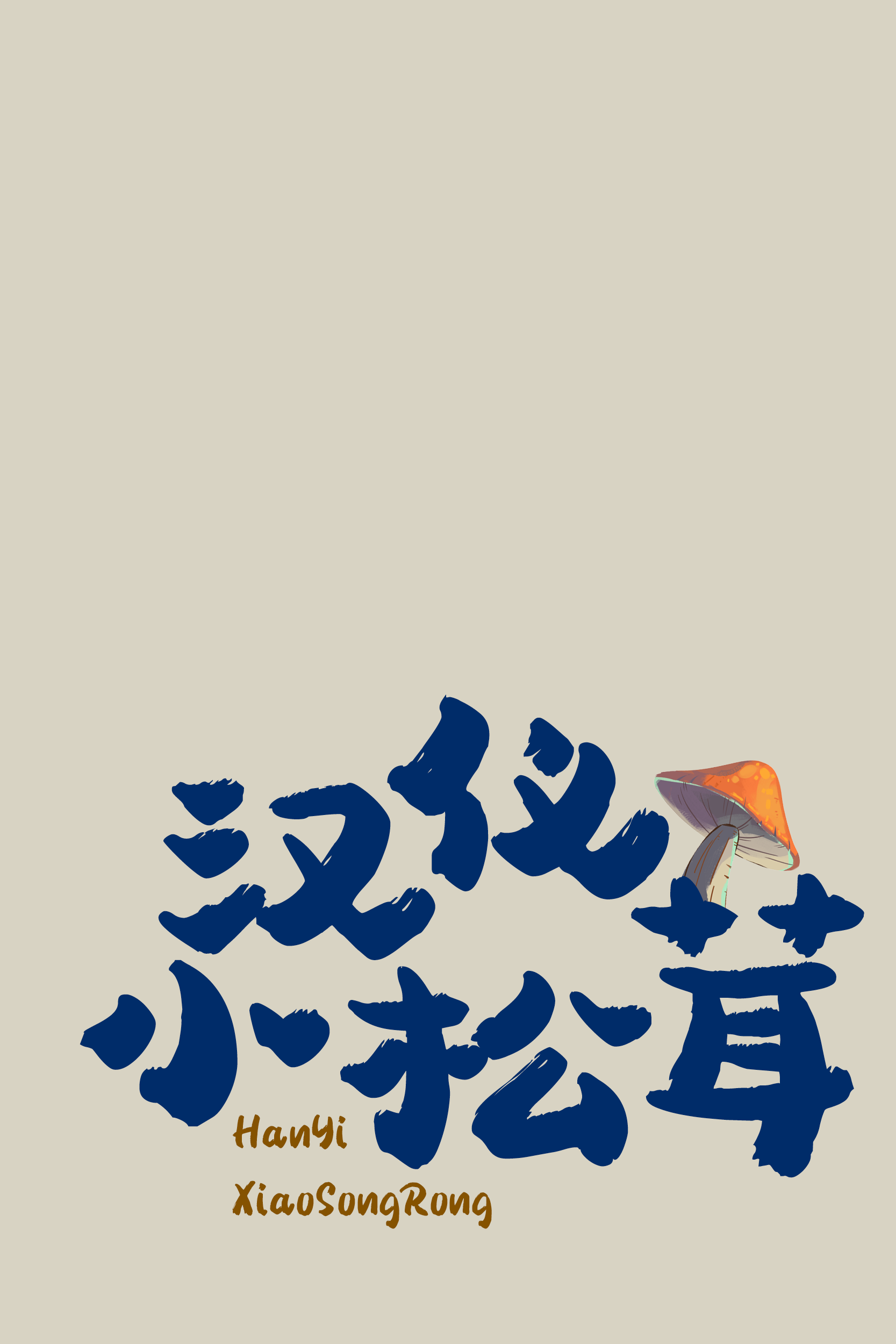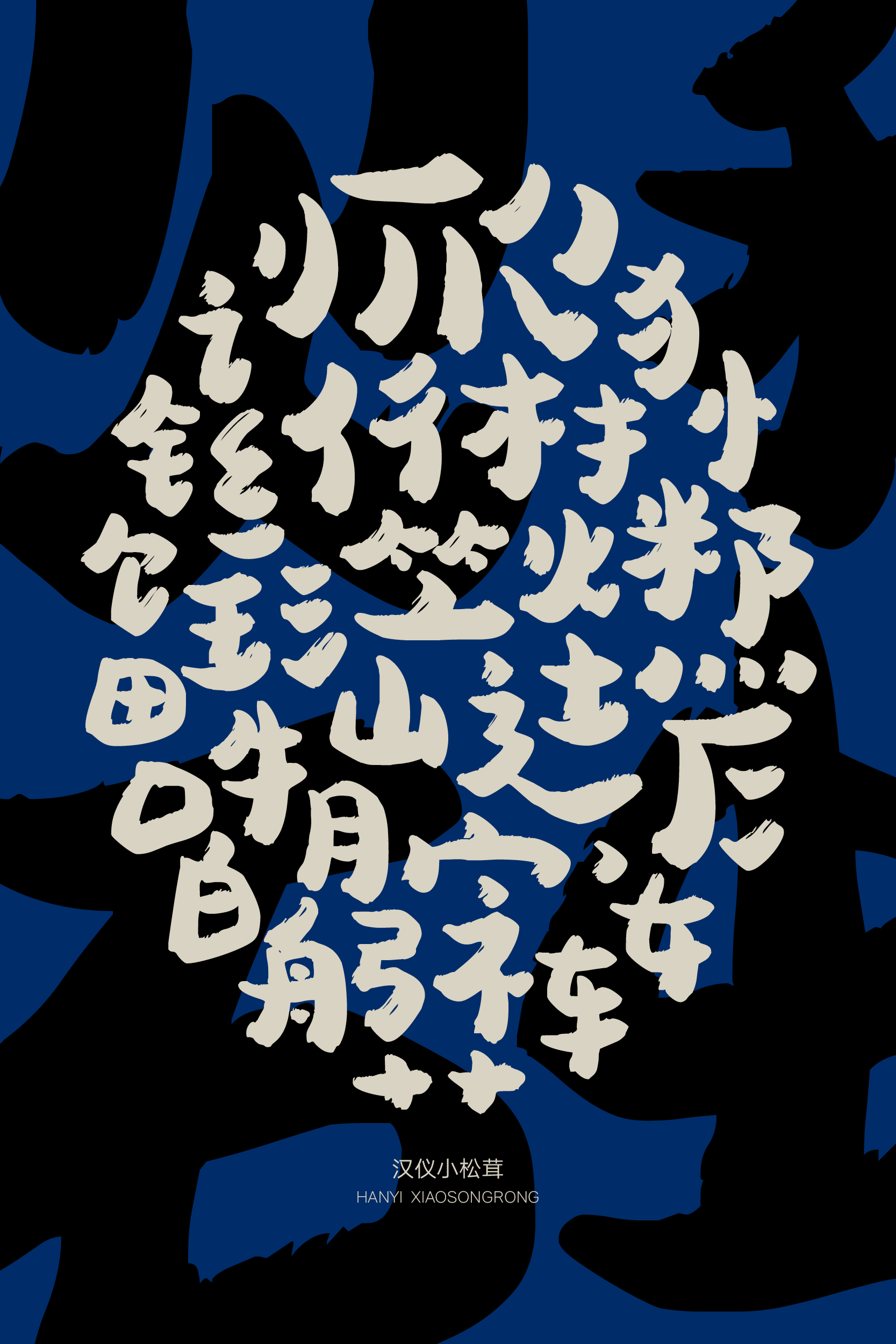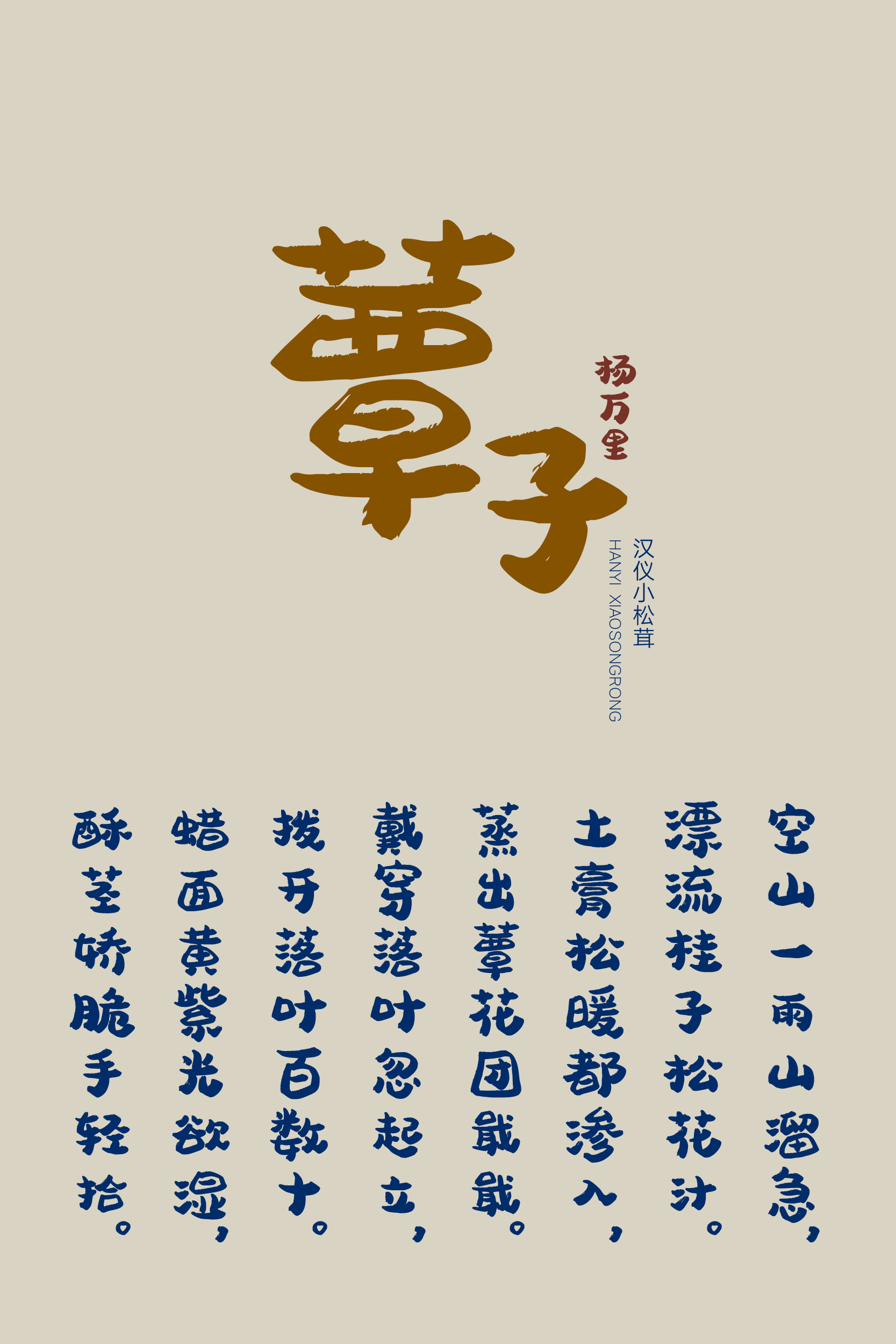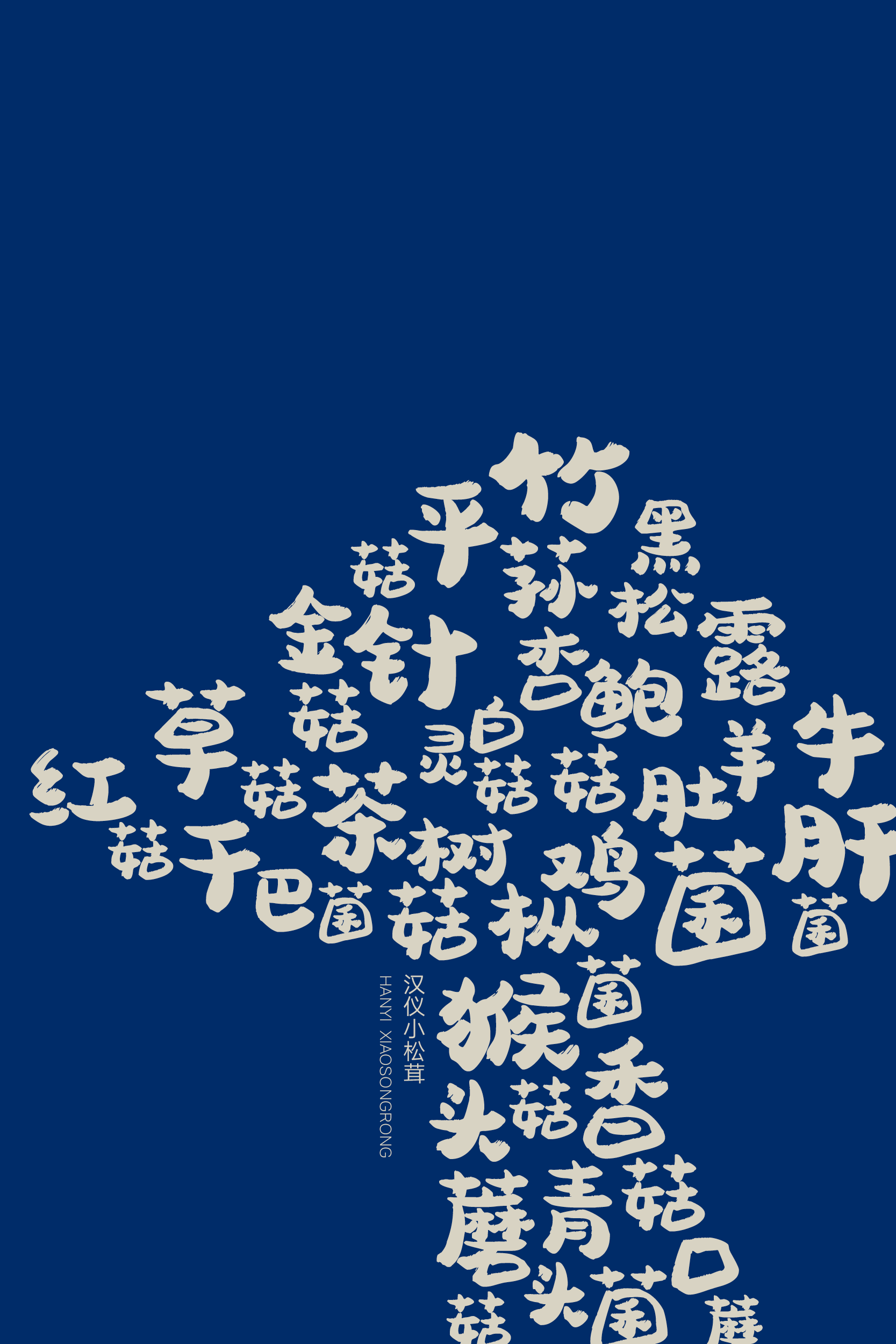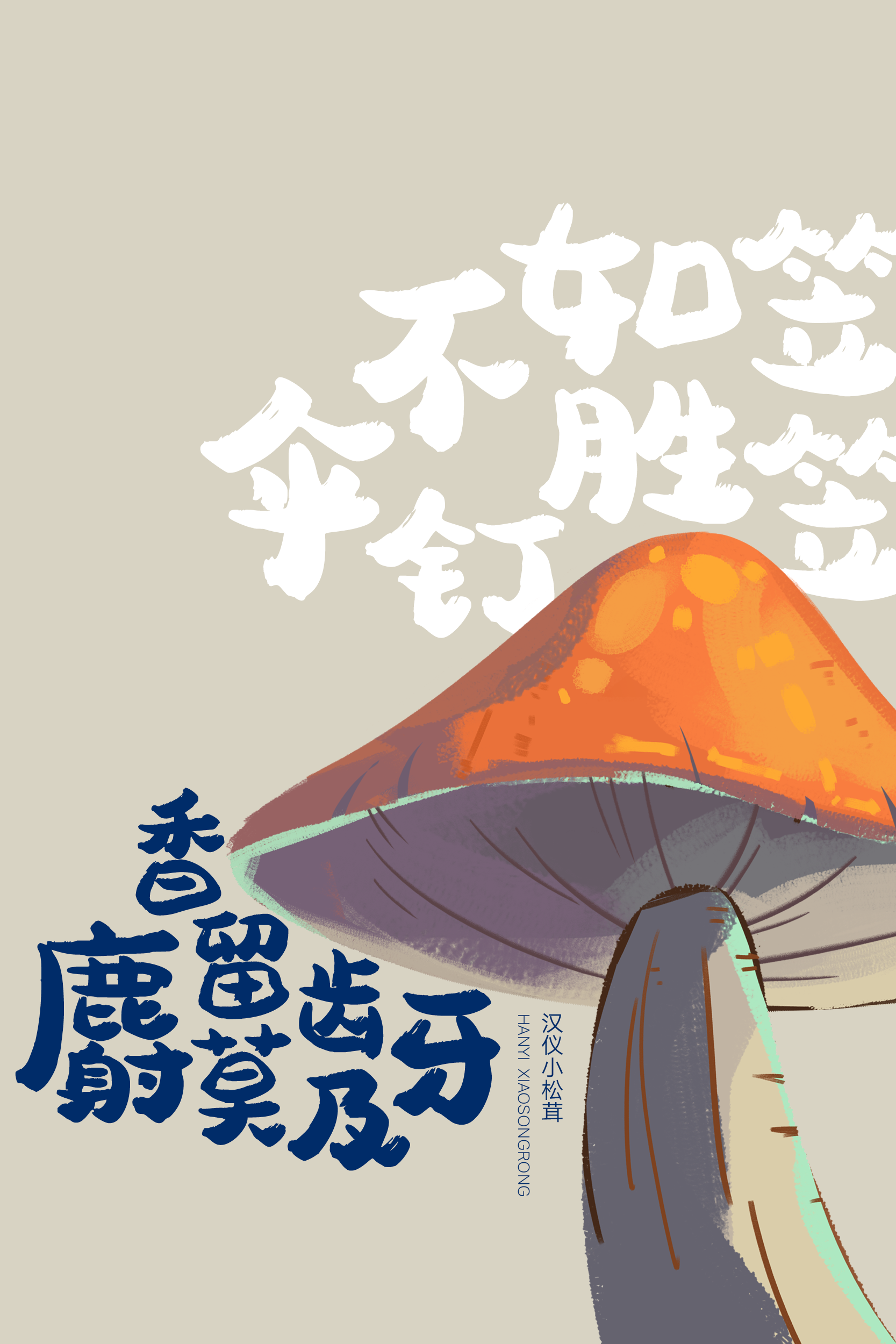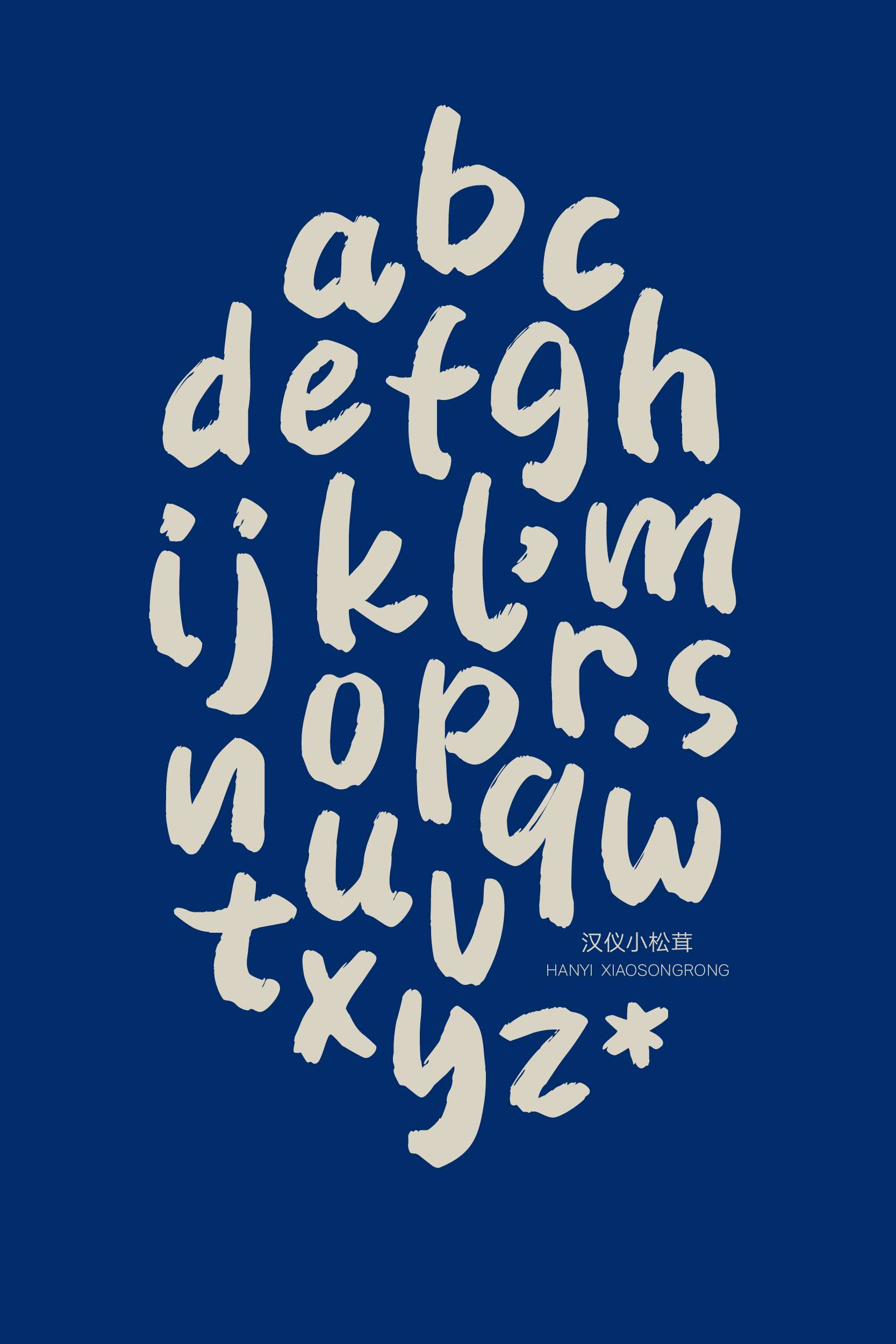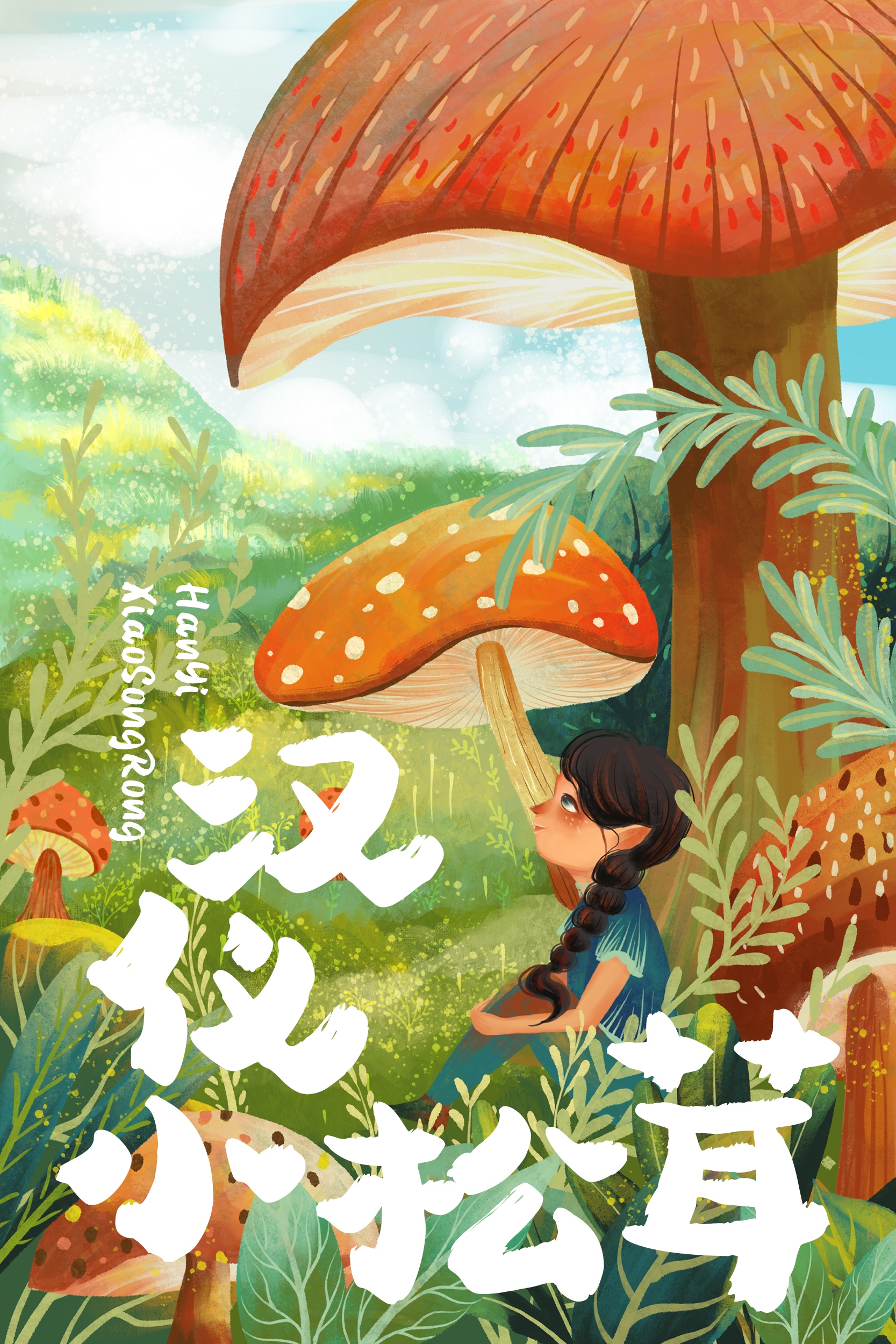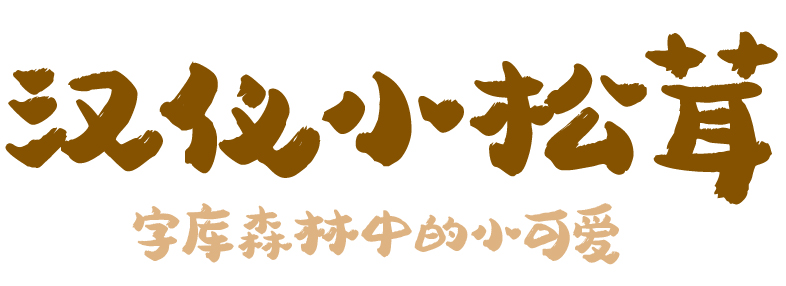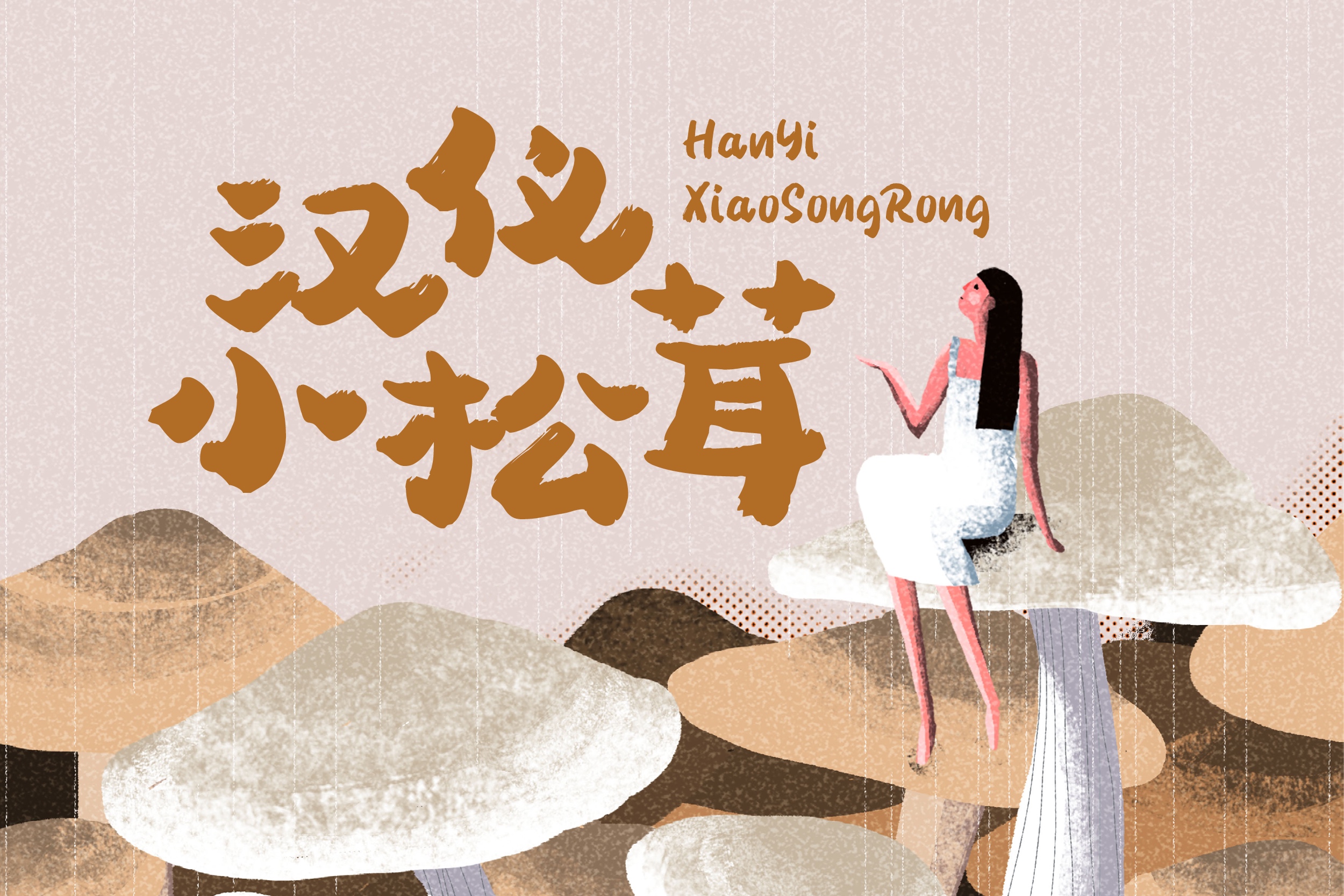
字库森林中的小可爱
手书
手写风 / 可爱 / 轻松 / 活泼 / 愉快
汉仪小松茸是由汉仪字库签约作者孙小松创作的一款轻松有趣的手写字体。它字形圆润,结构多变,笔画饱满,呈现出一种俏皮可爱的视觉效果。这款字体适用于产品包装、广告宣传、海报、书籍、杂志、餐饮等多种场景。
汉仪小松茸根据每一个字的字形来设计结构,不拘泥于统一的字面。 字面宽窄高低变化错落有致,重心居中稳定,无需专门排版即可呈现俏皮的效果。
汉仪小松茸主笔粗壮,像松茸肥美的菌柄,梯形的口字结构像松茸的菌盖,是雨季林间窜出的一朵朵小蘑菇。
字体笔画起收笔简洁直率,运笔略带弧度。右点和捺的末端上挑,使得排版效果更连贯,有“行气”。
汉仪小松茸西文部分也是用秀丽笔书写出的 Brush风格字体,天真可爱,丰富多变。中西文搭配和谐统一。